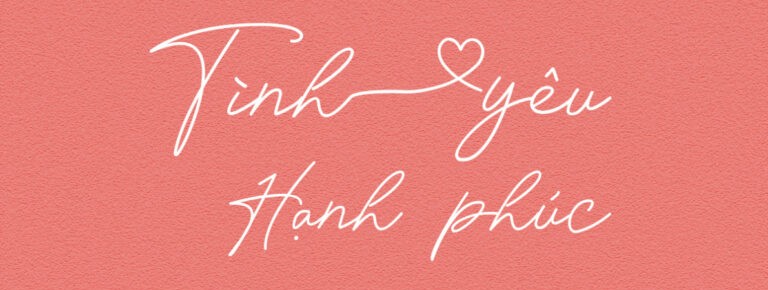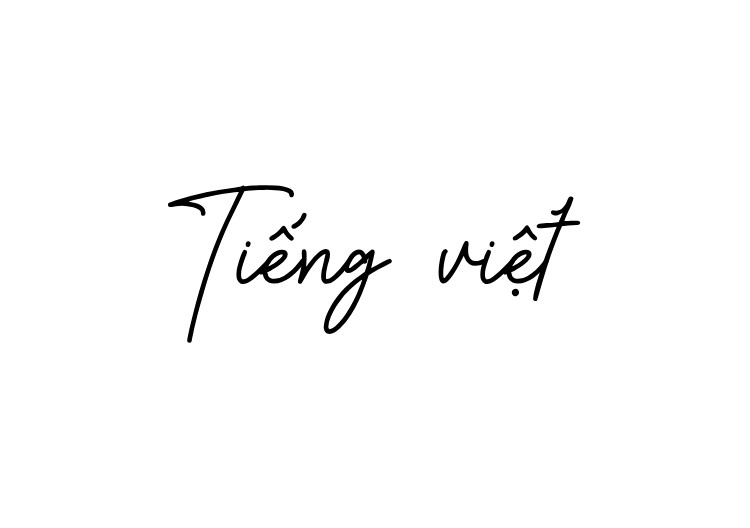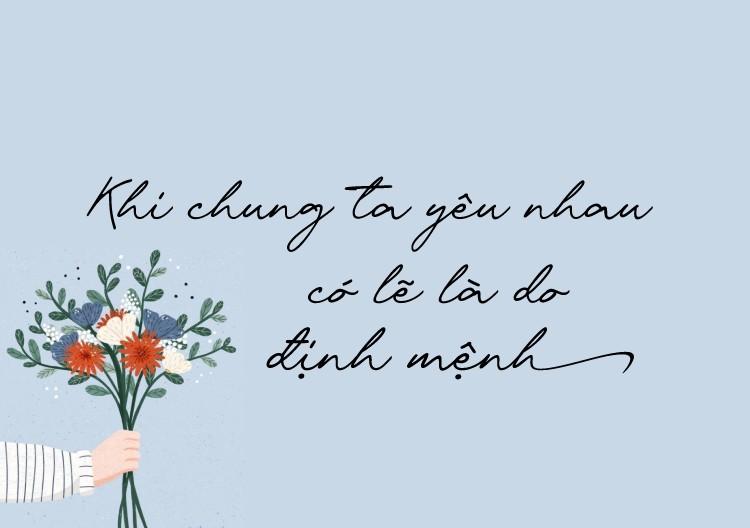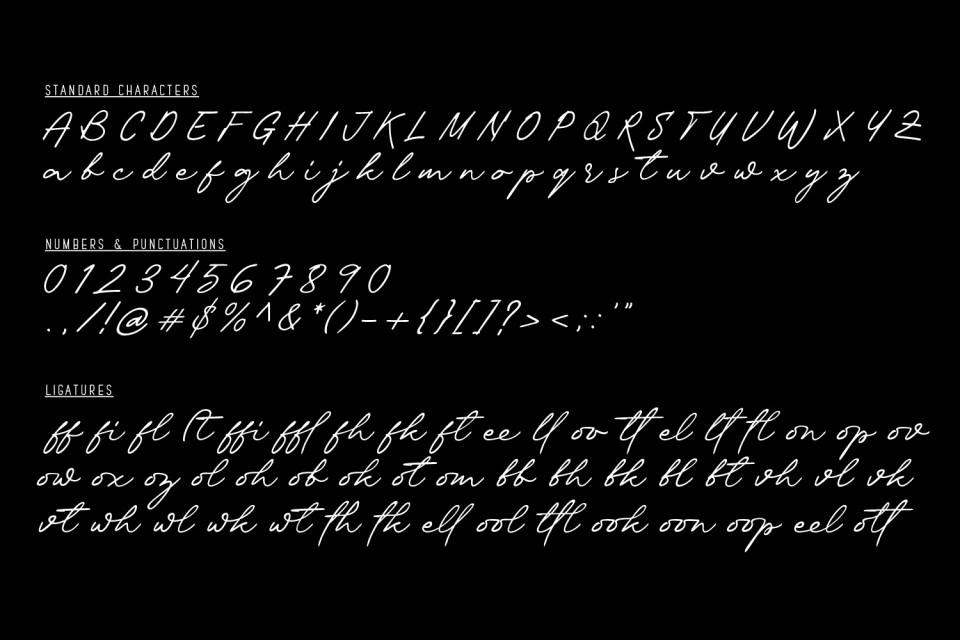
Font MJ là gì?
Font MJ (thường được biết đến qua các bộ phông của MJ Fonts) là dòng phông chữ mang đậm tính nghệ thuật, từ phong cách thư pháp (Calligraphy) đến các nét chữ vẽ tay bay bổng. Đây là sự lựa chọn cho các thiết kế yêu cầu sự mềm mại, lãng mạn và có tính cá nhân hóa cao. Font MJ giúp bản thiết kế thoát khỏi sự rập khuôn của các phông chữ văn phòng, mang lại hơi thở đầy tính sáng tạo cho sản phẩm.
Tuy nhiên, đặc trưng của các dòng font nghệ thuật như MJ là có nhiều nét nối và họa tiết phụ đi kèm. Nếu không được xử lý kỹ thuật tốt, khi in ấn trên các chất liệu khó như kim loại hay gốm sứ, nét chữ rất dễ bị nhòe mực. Tại In Viva, chúng tôi đã chọn lọc những font MJ có cấu trúc path ổn định, giúp các designer dễ dàng ứng dụng vào sản xuất thực tế mà không lo lỗi kỹ thuật.
Lưu ý: Khi sử dụng font MJ cho mục đích in nung men sứ, hãy đảm bảo khoảng cách giữa các nét nối đủ lớn để mực in không bị loang, giữ được vẻ thanh thoát của bộ chữ nghệ thuật.
Ứng dụng font MJ trong thiết kế và gia công in ấn
Sức hút từ những đường nét mềm mại của font MJ giúp các ấn phẩm trở nên đặc biệt và thu hút hơn:
- Thiết kế bao bì hộp socola: Những nét chữ MJ lãng mạn in ép kim đỏ trên nền hộp cứng đen hoặc trắng tạo nên sự tương phản đẳng cấp, rất phù hợp cho mùa Valentine hay kỷ niệm ngày cưới.
- Sản xuất túi giấy đựng trà và nông sản cao cấp: Font MJ mang lại cảm giác mộc mạc, thủ công (handmade), giúp các sản phẩm trà sạch, cafe hạt ghi điểm cộng lớn về sự chân thành đối với khách hàng.
- In logo lên bộ ấm chén gốm sứ: Hình ảnh logo dùng font MJ in nung ở nhiệt độ cao trên sứ Bát Tràng tạo nên một tác phẩm nghệ thuật thực sự, là sản phẩm đối ngoại vô cùng tinh tế.
- Gia công khắc laser sổ tay bìa gỗ: Các đường uốn lượn của font MJ khi được khắc chìm trên gỗ tạo độ sâu ấn tượng, bền bỉ theo thời gian và mang đậm dấu ấn cá nhân.